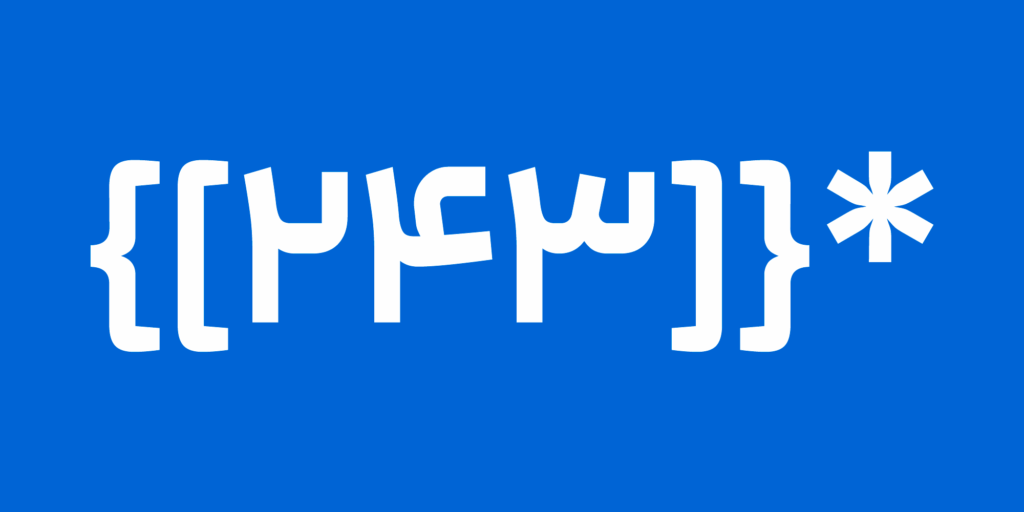
خانواده فونت پیدا
پیدا یکی از فونتهای فارسی مدرن و هندسی است که با ساختاری ساده، تمیز و خوانا طراحی شده و برای برندهایی که به دنبال هویتی امروزی و مینیمال هستند، انتخاب مناسبی به شمار میرود. تناسبات منظم حروف، فضای سفید مناسب و فرمهای کنترلشده باعث شده این فونت برای شروع طراحی لوگوتایپ بسیار کاربردی باشد. اگرچه پیدا بهتنهایی یک لوگوتایپ کامل نیست، اما پایهای خوب برای ساخت یک نشانه نوشتاری اختصاصی فراهم میکند.
ابتدا فاصلهگذاری حروف را دقیق تنظیم میکنم، سپس برخی اتصالات و انتهای حروف را بازطراحی میکنم تا فرم نهایی از حالت تایپشده خارج شود. در مرحله بعد با ایجاد تغییرات ظریف در تناسبات و جزئیات، لوگوتایپی میسازم که هویت مستقل و اختصاصی داشته باشد.